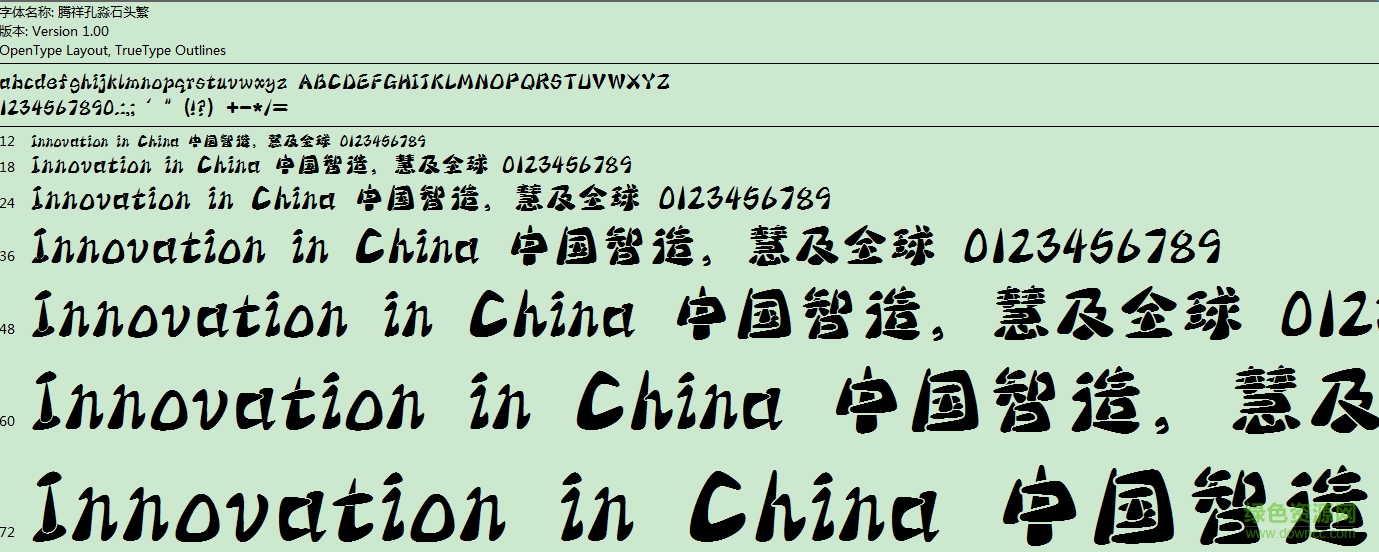
騰祥孔淼石頭繁
騰祥孔淼石頭繁體是一款騰祥出品的繁體字體,字形美觀有趣,美工設(shè)計(jì)、海報(bào)設(shè)計(jì)等方面都可以使用,小編為大家?guī)?lái)免費(fèi)下載地址,歡迎大家來(lái)綠色資源網(wǎng)踴躍下載哦!
騰祥孔淼石頭繁體
騰祥孔淼石頭繁體,一款非常有趣的字體,適用于廣告方面,字形工整,又充滿力量。